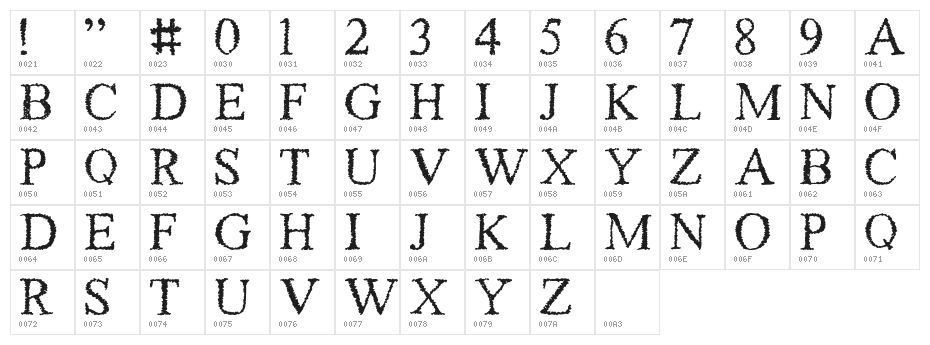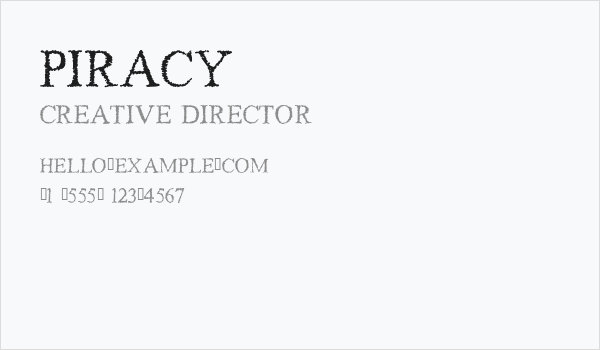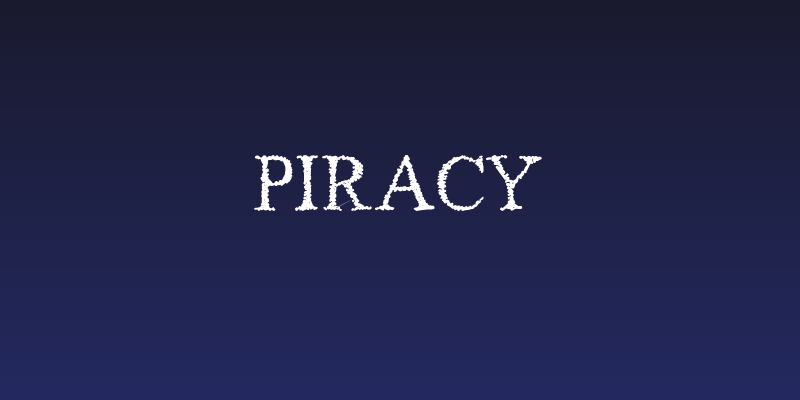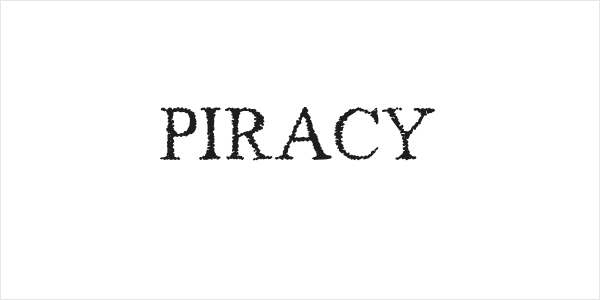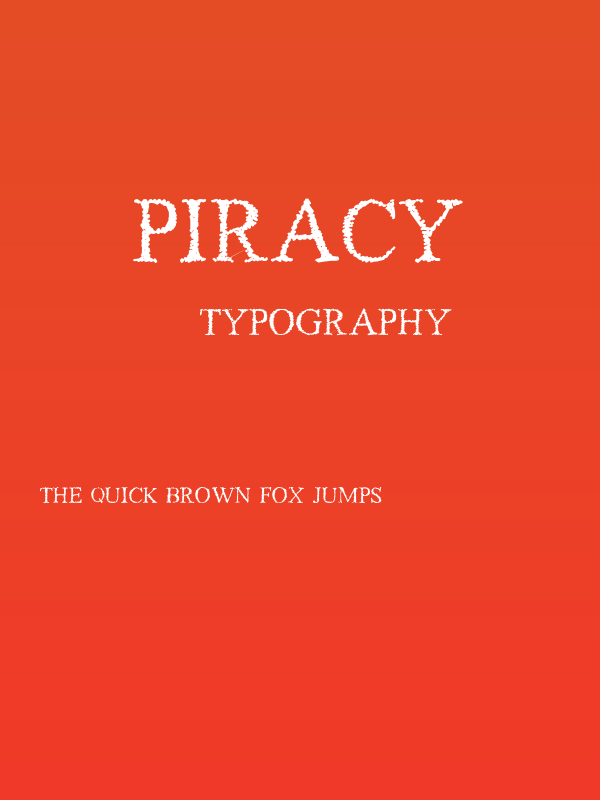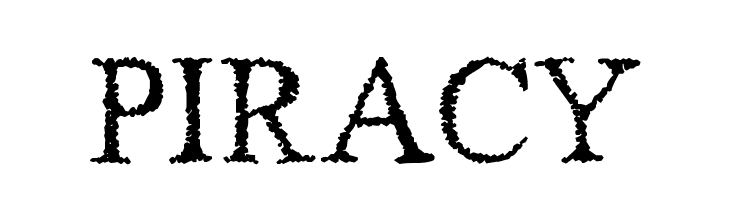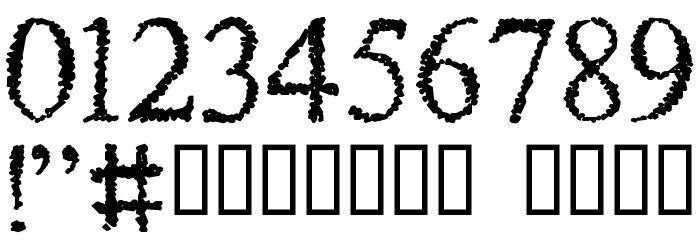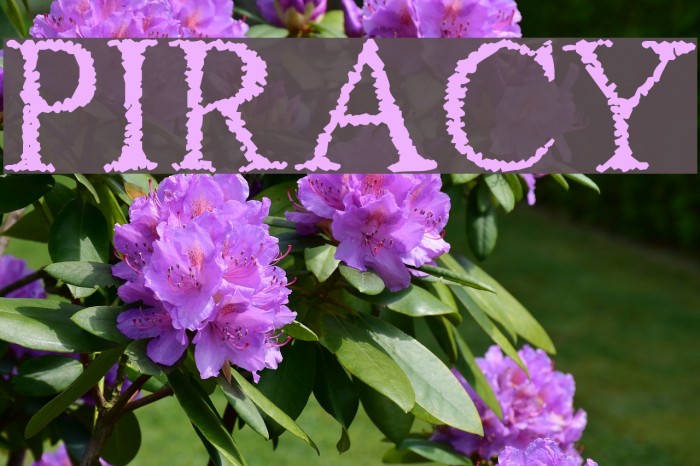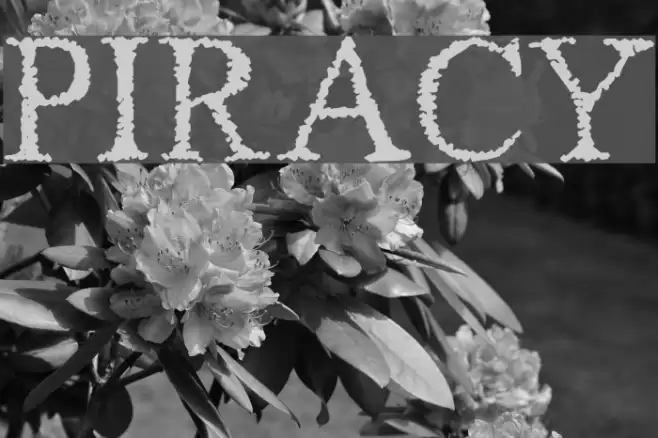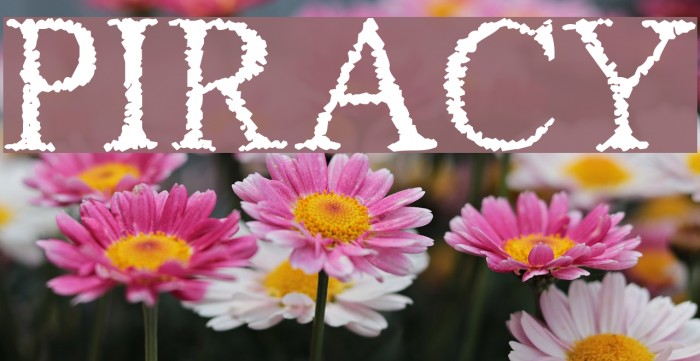
Piracy Font
✎ Distorted Eroded
| Categorii | Distorted Eroded |
| Proiecte propuse | Ideal for pirate-themed designs, adventure book covers, treasure maps, escape room branding, and vintage posters. |